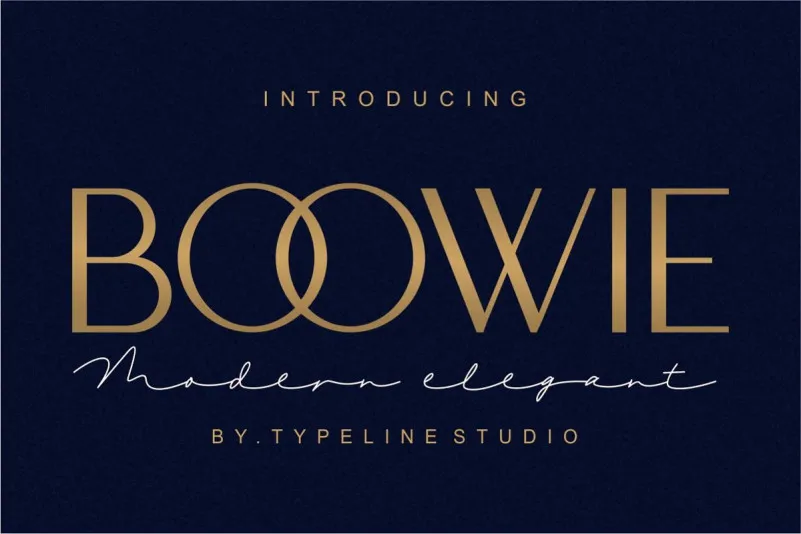
Boowie Sans Serif Font – Download Grátis
Introduzimos a Boowie Font. Esta é uma fonte premium criada pelo typeline studio, vendida na Creativemarket. Agora, você pode desfrutar dela gratuitamente para download. A Boowie Sans Serif Font apresenta uma versão regular e itálica de um sans serif minimalista. É perfeita para uso em logomarcas, impressões, colagens, texto do corpo e muito mais! Ela oferece um aspecto moderno com toques vintage a qualquer projeto. Com certeza vai adicionar um toque único e fresco a suas criações.